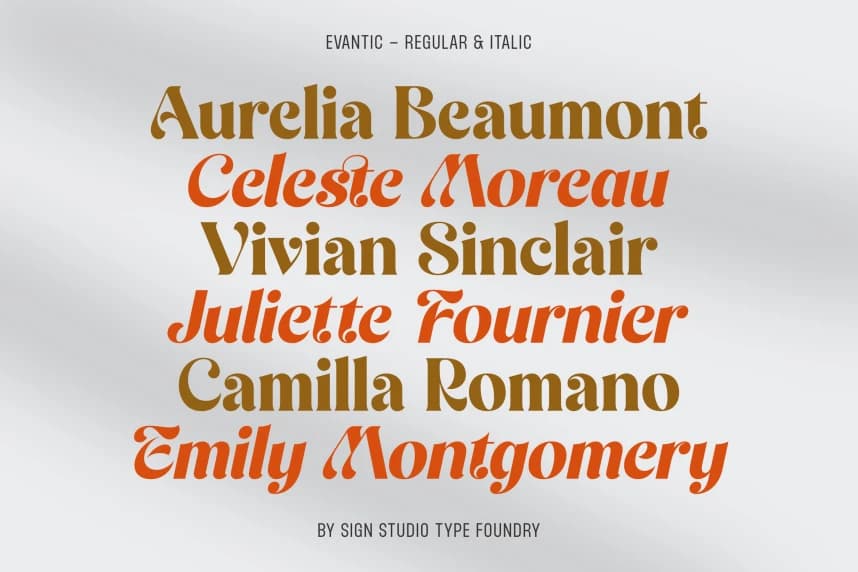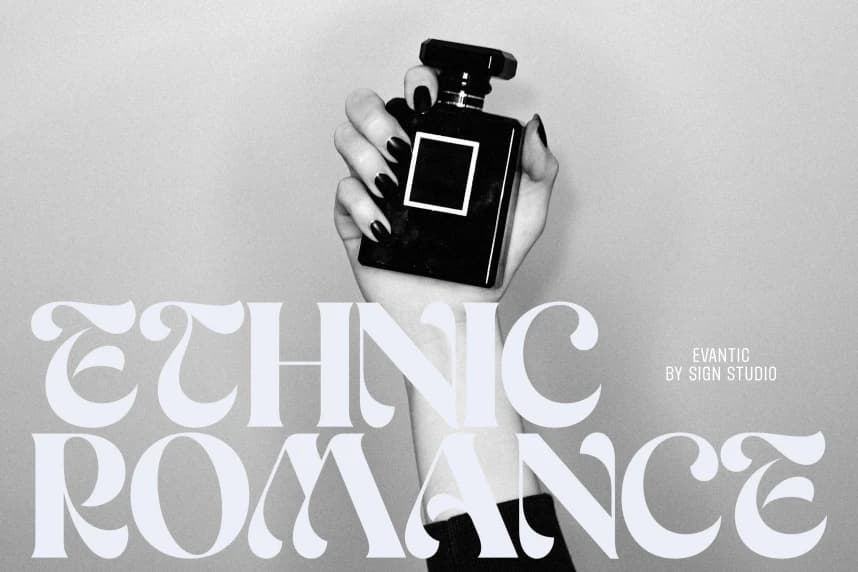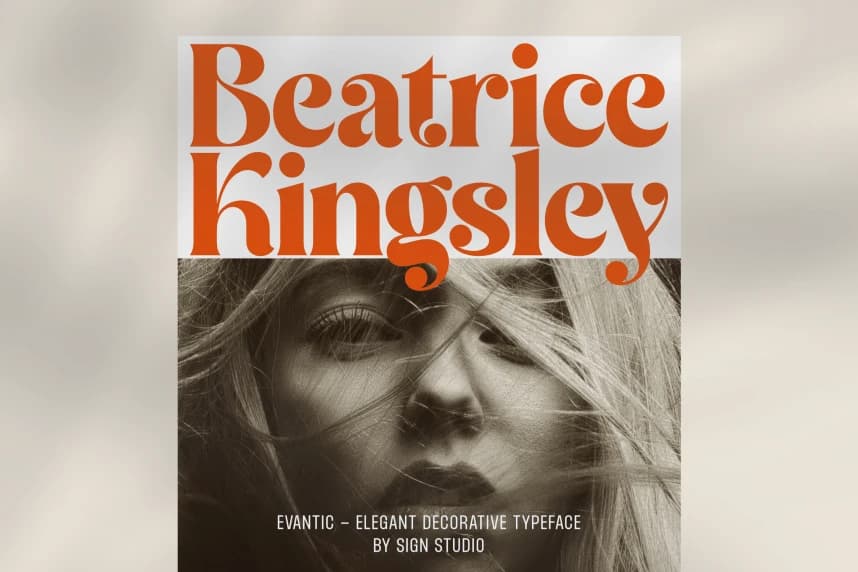
Evantic Serif Font
Evantic Serif Font, modern tasarıma rafine ve zamansız bir atmosfer katmak üzere tasarlanmış zarif bir serif yazı tipidir. Zarif eğrileri, dengeli oranları ve şık detaylarıyla Evantic, hem klasik hem de çağdaş hissedilen sofistike bir görünüm sunar.
Evantic Serif Font, modern tasarıma zarif ve zamansız bir atmosfer kazandırmak üzere tasarlanmış zarif bir serif yazı tipidir. Zarif eğrileri, dengeli oranları ve şık detaylarıyla Evantic, hem klasik hem de çağdaş hissiyat veren sofistike bir görünüm sunar.